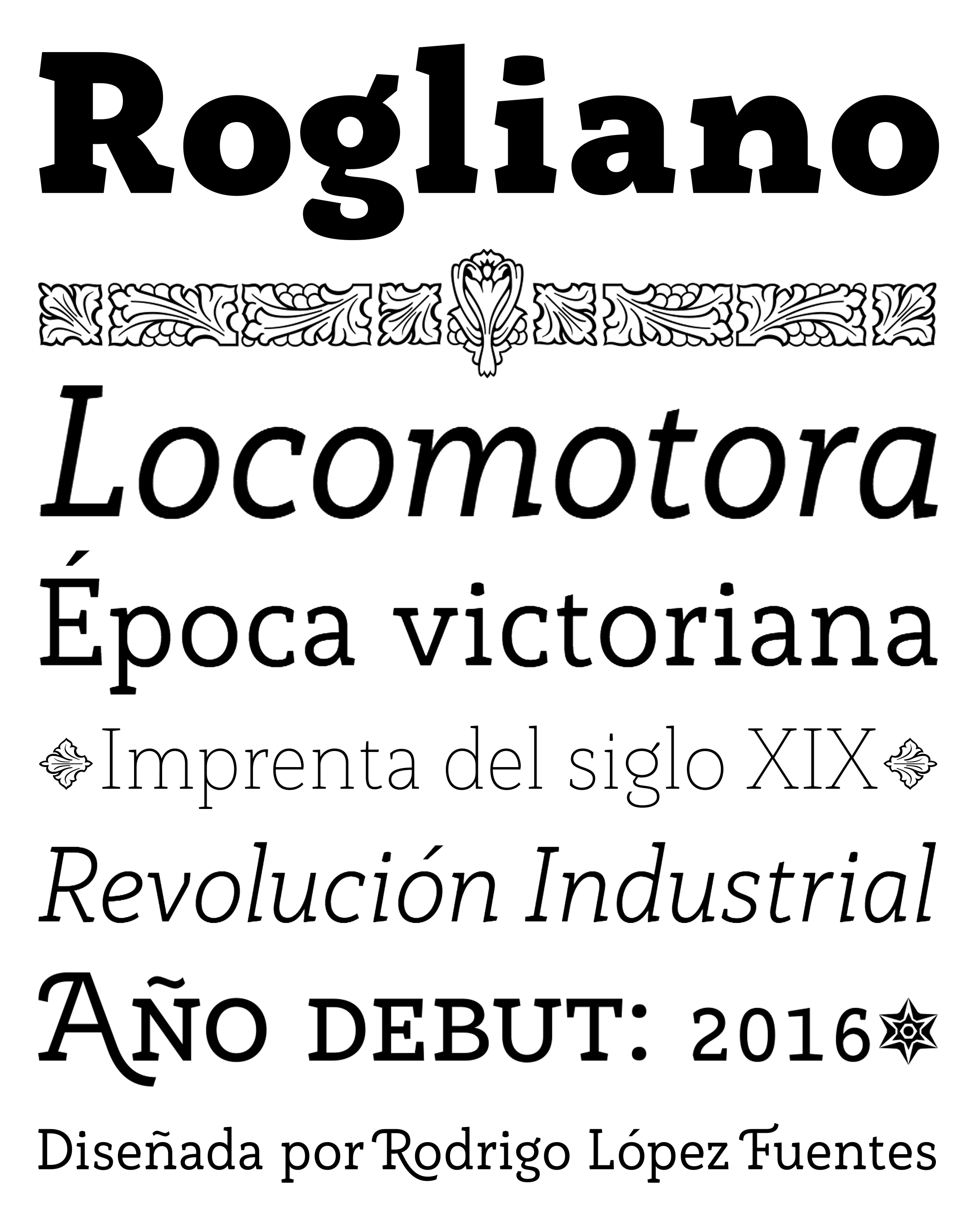
Rogliano
| Año | 2016 |
| Créditos | Rodrigo López Fuentes |
| Descripción | Rogliano responde al principio clásico de los alfabetos fuertes y directos de la época de la Revolución Industrial, a la vez que alimenta el texto de un ambiente cálido, se toma la libertad de coquetear con la letra y los carteles litográficos de la época victoriana. |
| Clasificación | Texto |
| Familia(s) | Slab |
| Estilos | 14 |
| Fundidora | Tipotype |